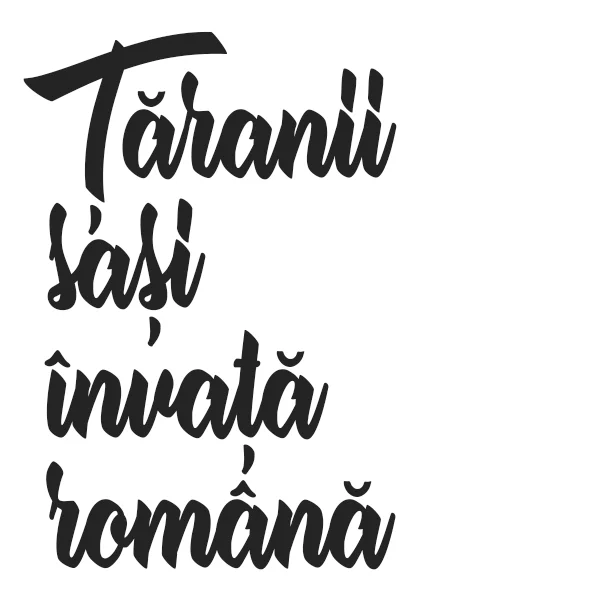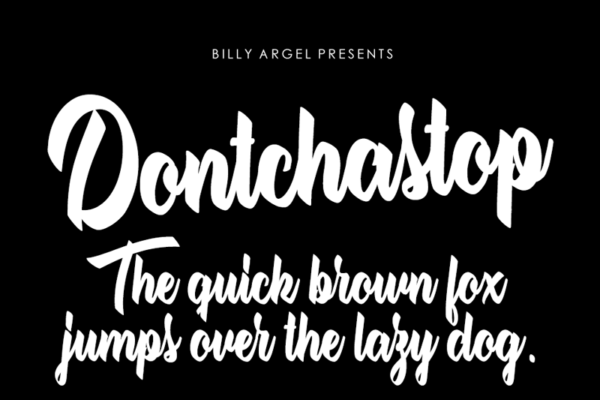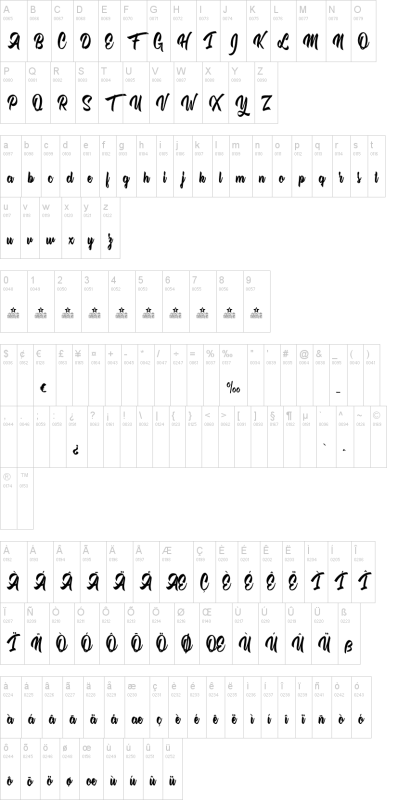
Categorie: Brush
perfect
perfect pentru decupaj litere
Foarte caligrafic
foarte frumos felicitari pt scrisul deosebit
foarte frumos felicitari realizatorului
foarte bun
util